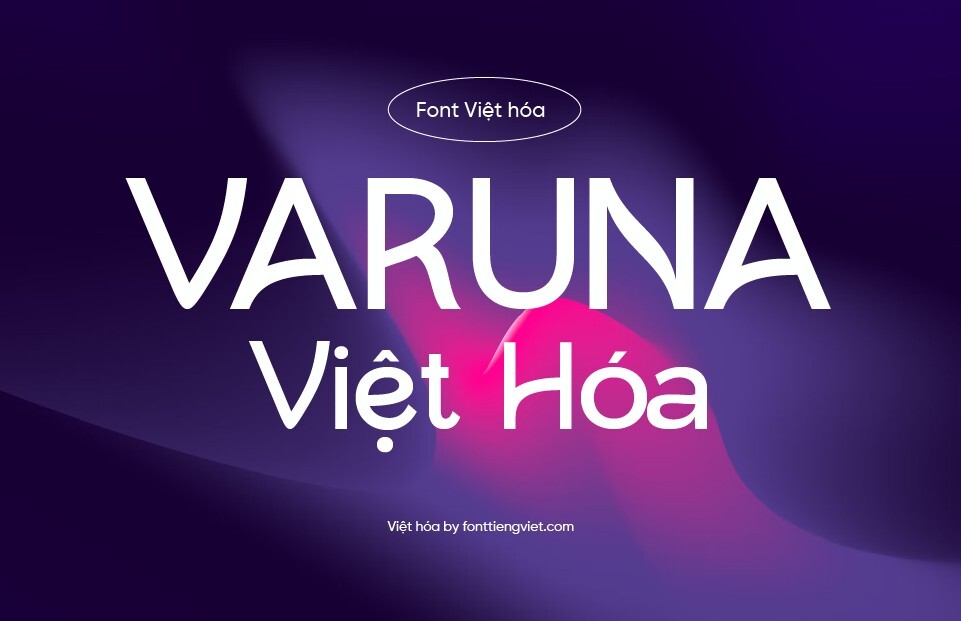
Font Việt hóa 1FTV VIP Varuna
Giới thiệu về Font Việt hóa 1FTV VIP Varuna trong thiết kế hiện đại
Trong thế giới sáng tạo nội dung số, việc lựa chọn một Font Miễn Phí chất lượng luôn là ưu tiên hàng đầu của các nhà thiết kế đồ họa. Font Việt hóa 1FTV VIP Varuna nổi lên như một giải pháp tối ưu, mang lại vẻ đẹp hiện đại nhưng vẫn giữ được nét tinh tế cần thiết cho các dự án tiếng Việt. Đây là bộ font được tinh chỉnh kỹ lưỡng về dấu câu, giúp người dùng không còn lo lắng về lỗi hiển thị khi soạn thảo văn bản. Đối với học sinh, sinh viên hay những người mới bắt đầu làm quen với thiết kế, bộ font này cung cấp một công cụ mạnh mẽ để làm nổi bật thông điệp truyền tải trên các ấn phẩm truyền thông hay slide bài giảng. Sự xuất hiện của 1FTV VIP Varuna đã giúp cộng đồng thiết kế tại Việt Nam có thêm lựa chọn phong phú, đáp ứng nhu cầu ngày càng cao về thẩm mỹ thị giác và tính chuyên nghiệp trong từng nét chữ.
Đặc điểm nổi bật của bộ Font Việt hóa 1FTV VIP Varuna
Thiết kế đa năng và tính ứng dụng cao
Bộ Font Việt hóa 1FTV VIP Varuna sở hữu phong cách thiết kế không chân (sans-serif) thanh thoát, tạo cảm giác thân thiện và dễ đọc trên cả màn hình điện thoại lẫn các bản in giấy. Các đường nét của font chữ được chăm chút tỉ mỉ, tạo nên sự cân bằng hoàn hảo giữa các khoảng cách chữ cái. Điều này đặc biệt quan trọng khi bạn cần trình bày những đoạn văn bản dài mà vẫn muốn giữ cho người đọc không cảm thấy mỏi mắt. Ngoài ra, tính năng “VIP” trong tên gọi của font cũng ám chỉ chất lượng cao cấp với khả năng hỗ trợ nhiều định dạng khác nhau, giúp việc tích hợp vào các phần mềm phổ biến như Photoshop, Illustrator hay Canva trở nên dễ dàng và mượt mà hơn bao giờ hết.
Tối ưu hóa tiếng Việt và khả năng hiển thị
Một trong những điểm yếu của nhiều font chữ quốc tế khi sử dụng tại Việt Nam là hệ thống dấu tiếng Việt thường bị lỗi hoặc không đồng bộ với thiết kế gốc. Tuy nhiên, với Font Việt hóa 1FTV VIP Varuna, mọi vấn đề này đã được giải quyết triệt để. Các dấu thanh như sắc, huyền, hỏi, ngã, nặng được đặt ở vị trí hợp lý, đảm bảo tính thẩm mỹ và sự rõ ràng cho văn bản. Font chữ này cực kỳ phù hợp cho các thiết kế tiêu đề, banner quảng cáo, hoặc thậm chí là làm font chữ chủ đạo cho các trang web giáo dục. Khả năng hiển thị sắc nét của nó giúp nâng tầm thương hiệu cá nhân và tổ chức một cách hiệu quả, tạo ấn tượng mạnh mẽ ngay từ cái nhìn đầu tiên với khách hàng và độc giả.
Kết luận về giá trị của Font Việt hóa 1FTV VIP Varuna
Tóm lại, việc sở hữu bộ Font Việt hóa 1FTV VIP Varuna trong bộ sưu tập thiết kế là một quyết định vô cùng đúng đắn cho bất kỳ ai yêu thích cái đẹp và sự chỉn chu. Nó không chỉ đơn thuần là những ký tự trên màn hình, mà còn là phương tiện truyền tải cảm xúc và ý tưởng một cách trọn vẹn nhất. Nếu bạn đang tìm kiếm những tài nguyên chất lượng, hãy truy cập ngay Font Miễn Phí, Font Việt Hóa, Font Việt hóa 1FTV VIP Varuna để cập nhật thêm nhiều mẫu chữ độc đáo khác. Hãy để sự sáng tạo của bạn bay xa hơn với những đường nét chữ chuyên nghiệp, góp phần xây dựng một cộng đồng thiết kế Việt Nam ngày càng phát triển và văn minh hơn trong tương lai gần.